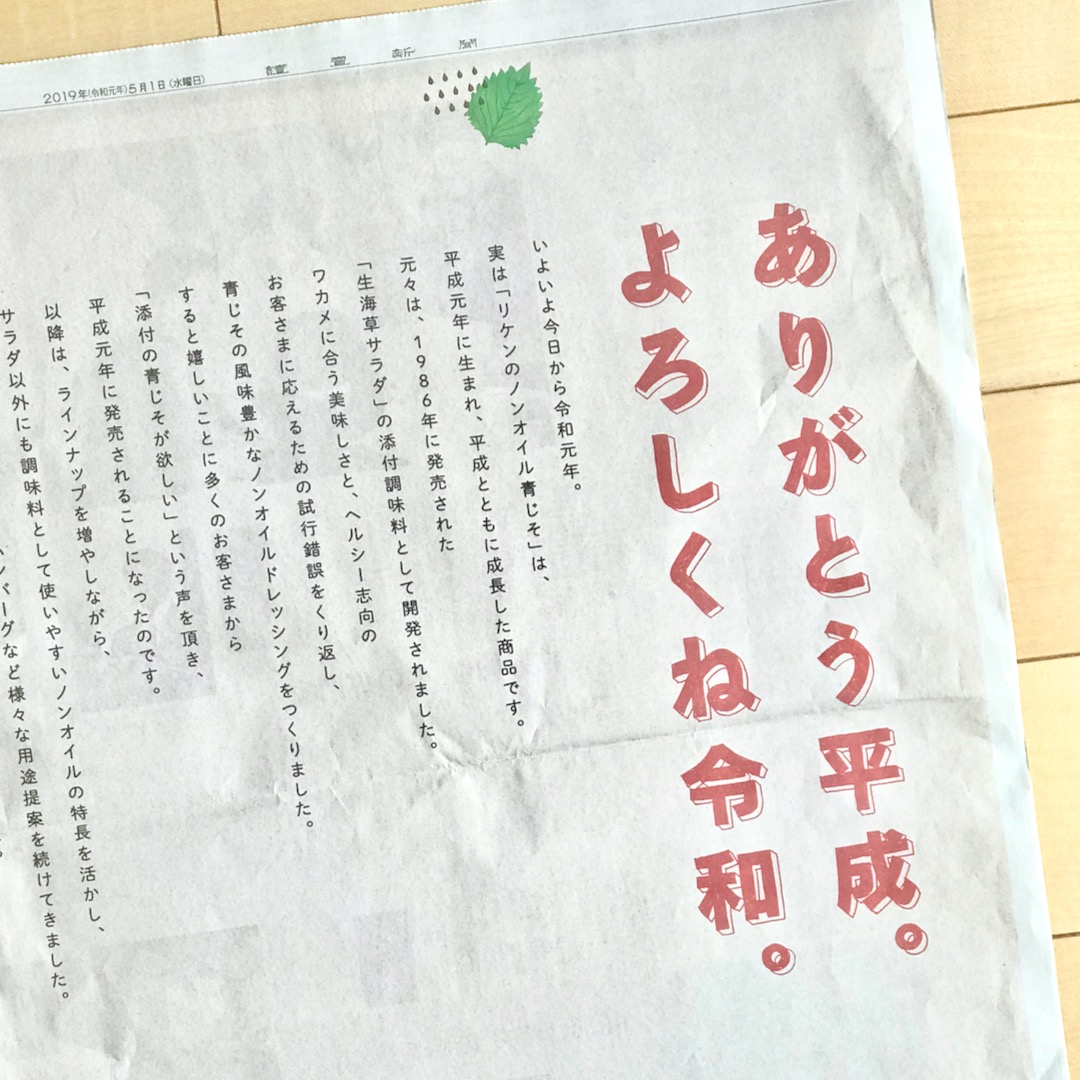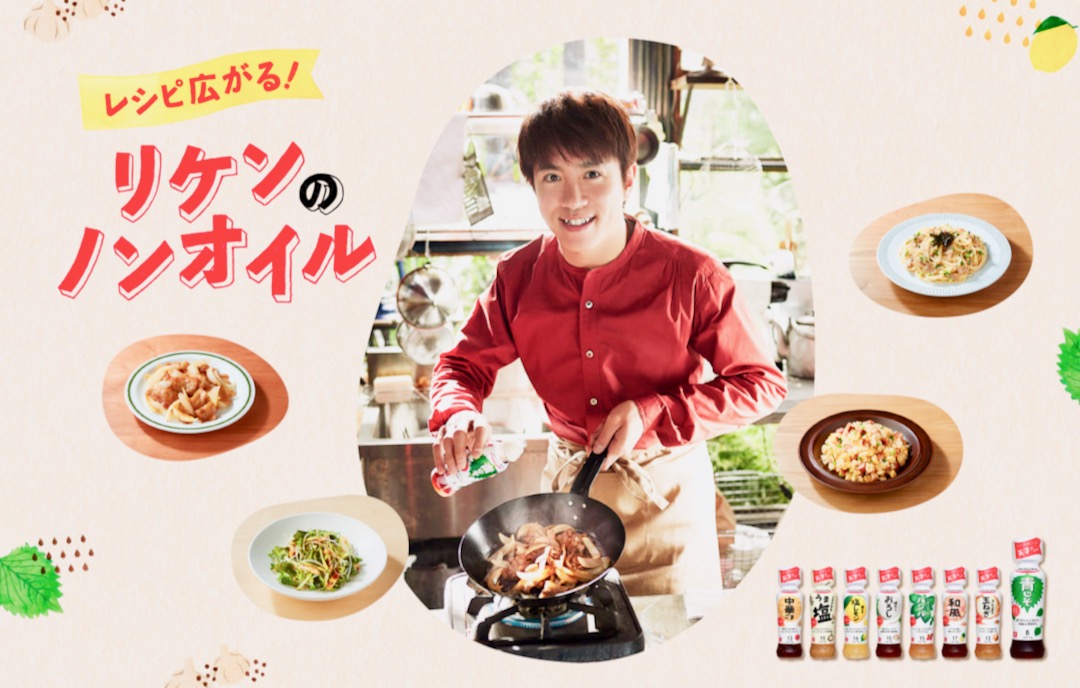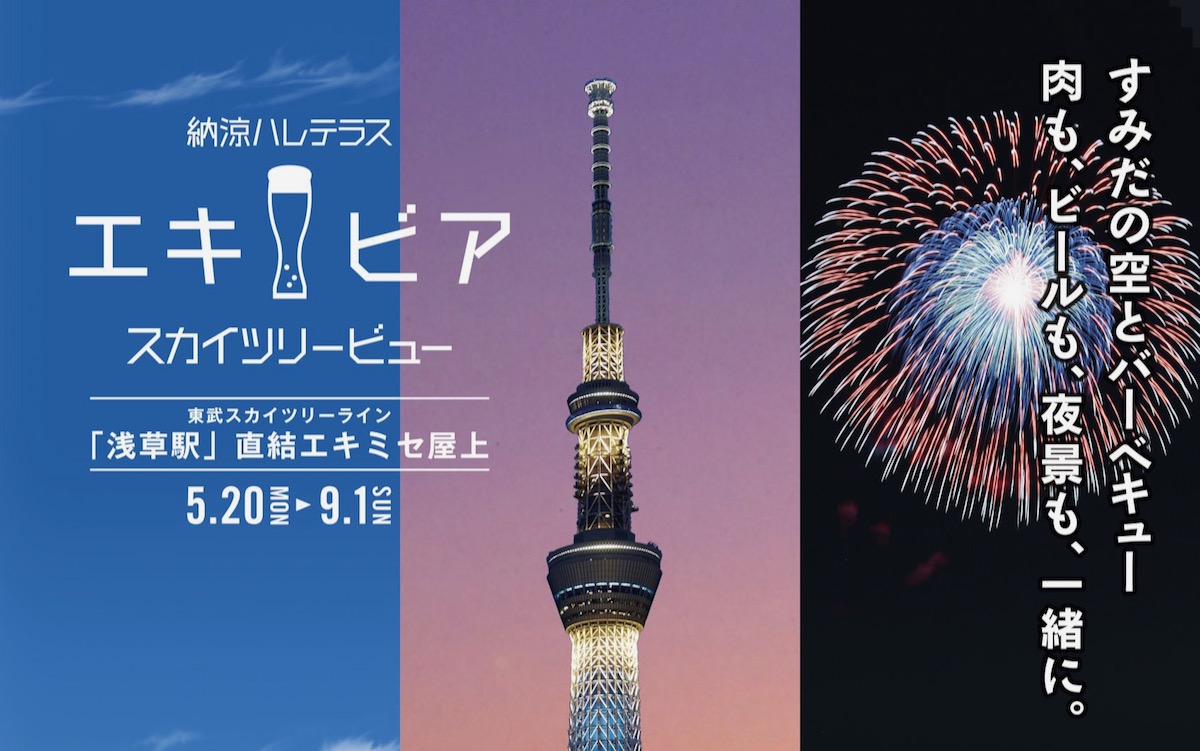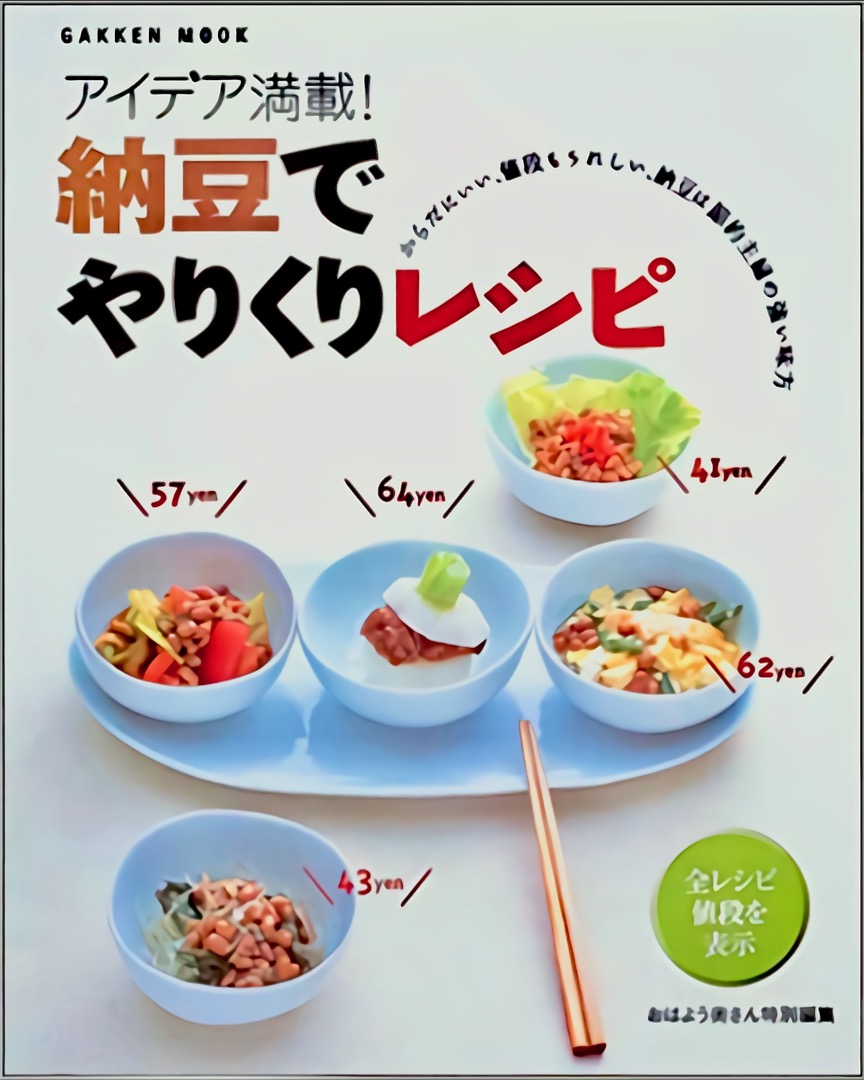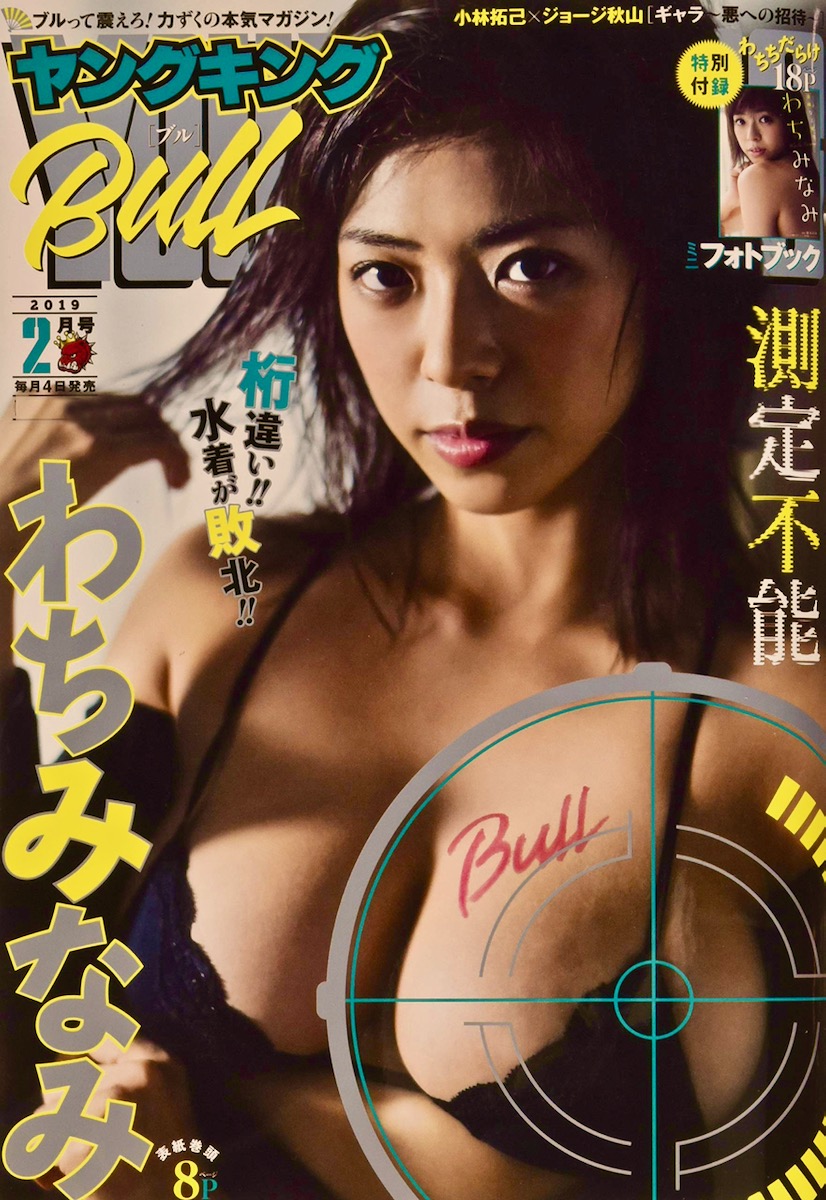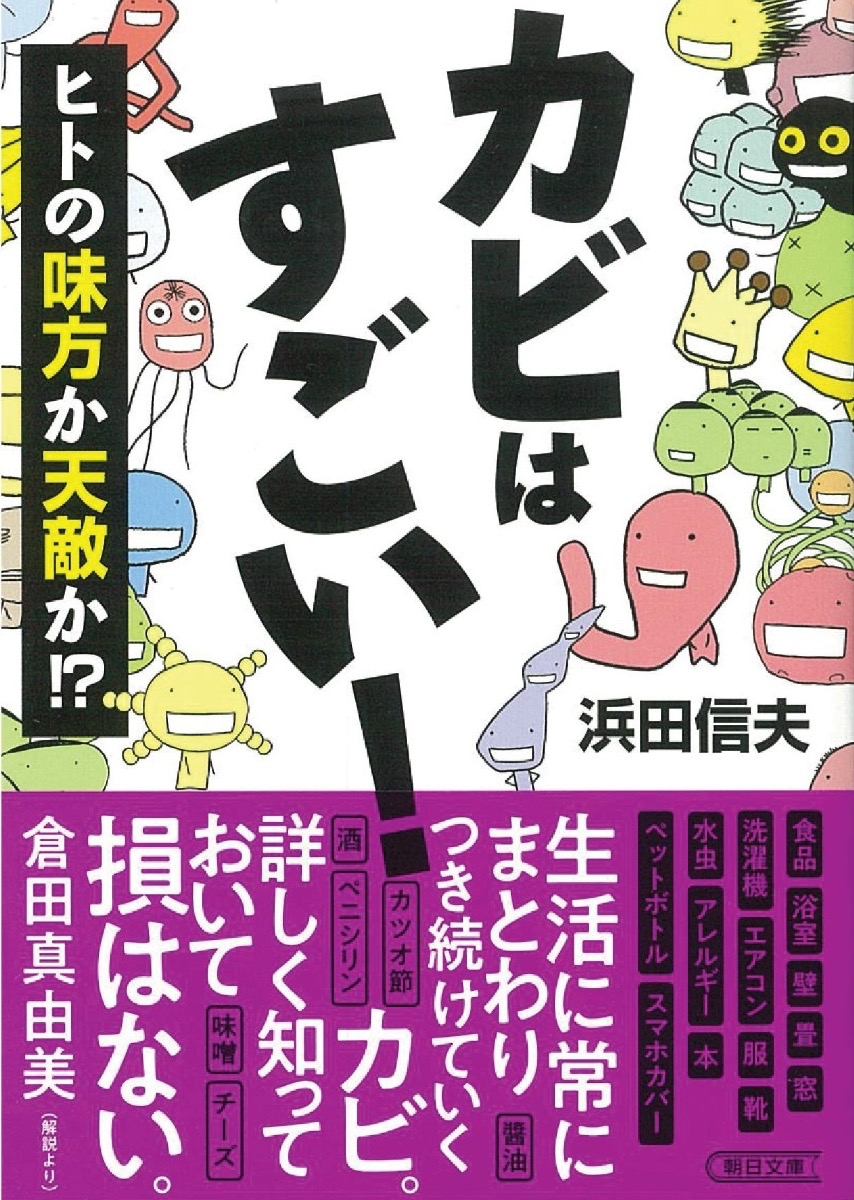
広告画像 さとうゆたか
全農のサイトの広告画像だと思う。
墨東ルイカ-07かな…。
AdobeFontsを利用している感じだ。
テレビ番組 さとうゆたか
テレビ東京の大食い王決定戦。
観光地のPDF さとうゆたか
イルカウォッチングのPDF表紙画像。
大小全ての文字に墨東ルイカ-07が使われている。
本の表紙 さとうゆたか
書名:登り続ける、ということ。
著者:野口 健
発行:学研プラス
コンサートのポスター さとうゆたか
知人のブログで発見した。
タイトルの字詰がちょっと甘いけど…。
ボニージャックス コンサート
~昭和歌暦~
本の表紙 さとうゆたか
書名:アブラハムものがたり 「みんなの聖書・絵本シリーズ」やくそくをしんじて
著者:藤本四郎、日本聖書協会
発行:日本聖書協会
書名:せかいのはじまり
著者:藤本四郎、日本聖書協会
発行:日本聖書協会
漫画のサブタイトル takumi
COMIC メテオで掲載されている漫画『邪神ちゃんドロップキック』の目次です。
作中のサブタイトルでも同様に「墨東」書体が採用されています。
ファミマの前に さとうゆたか
「おでん」の、のぼり旗。
約2年前にも見かけた。
YouTube動画 さとうゆたか
タイプラボのフォントはYouTuberにも好かれているようだ。
動画の中には、ニタラゴフォントが大量に使われている。
付録の冊子 さとうゆたか
新聞の購読者に配布されるもの。